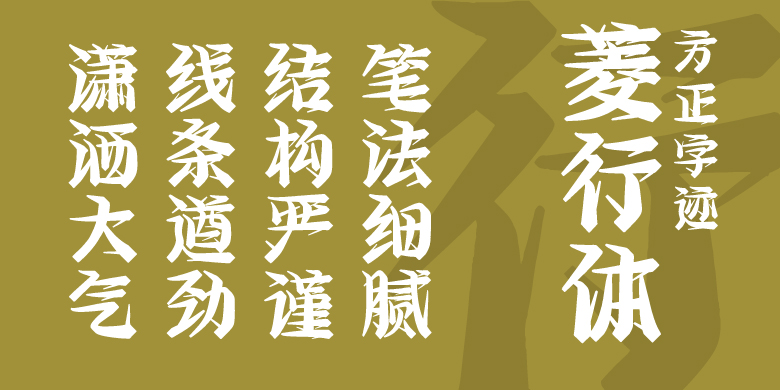
方正字迹-菱行体
方正字迹-菱行体,这款字体结构工整、笔画清晰,兼顾美观与易读性,适用于标题、正文、海报、包装、LOGO 等多种场景。字形优雅稳定,风格百搭耐看,适配日常排版与创意设计,让文字呈现更舒适、更具质感。方正字迹-菱行体一笔一画,皆是细节,以均衡的比例、流畅的线条打造舒适视觉体验,字形端正大气,风格简约现代。无论是商业设计、品牌宣传还是日常排版,都能轻松驾驭,让文字更有格调与力量。方正字迹-菱行体字体下载。
方正字迹—菱行体,因菱形笔触本身就有一种几何感,所以注定该字体不是传统意义上守旧的行书,而可以呈现出一种比较新并且整体看上去非常英气的书写字体,而这些恰巧贴合最近流行的“新中式”风格——中式元素与现代笔触的巧妙兼柔~
该字体笔法细腻,结构严谨,线条遒劲,潇洒大气,适用于品牌标志、招牌、影视综艺、游戏、产品包装及促销广告设计,且尤其适合于新中式品牌标志或者新中式产品包装使用。